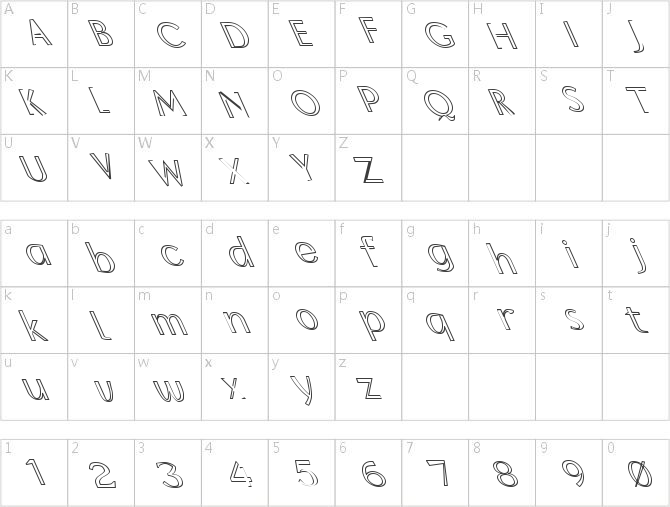
FZ BASIC 11 HOLLOW LEFTY 詳情頁
FZ BASIC 11 HOLLOW LEFTY字體字庫是一款讓人賞心悅目、百看不厭的英文字體,適合各類廣告和產(chǎn)品包裝設(shè)計(jì)應(yīng)用,字體大小0.06MB,格式為ttf字體,上傳用戶是afig,作者/版權(quán)方為未知